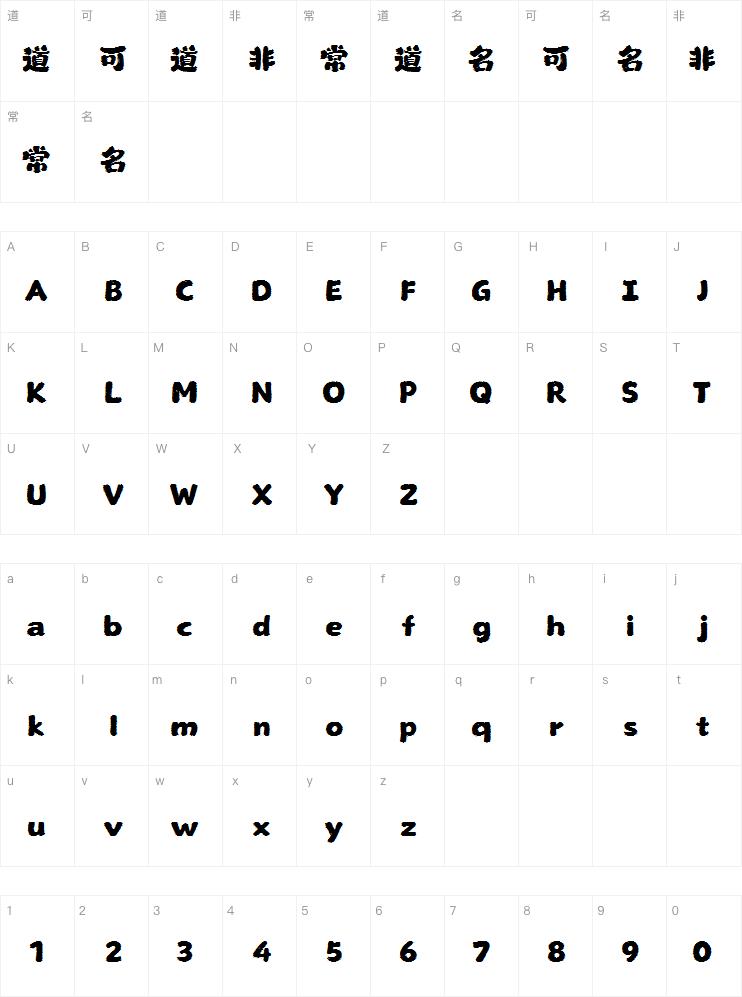
山海冰镇西瓜手书,是一款全新的卡通+古风毛笔字体,包含汉字9169个,符号200+个。该字体童趣可爱,结构多变灵动,字形活泼清新,造型生动有趣,具有灵活的适用性,天真俏皮又不失时尚感;同时兼具古风元素,古朴典雅,以毛笔风格的表现形式,使字体更别具一格,笔画的飞白效果使字体的气息更加流畅,笔画间的关系密不可分,同时也增加了字体的自由俏皮之感。